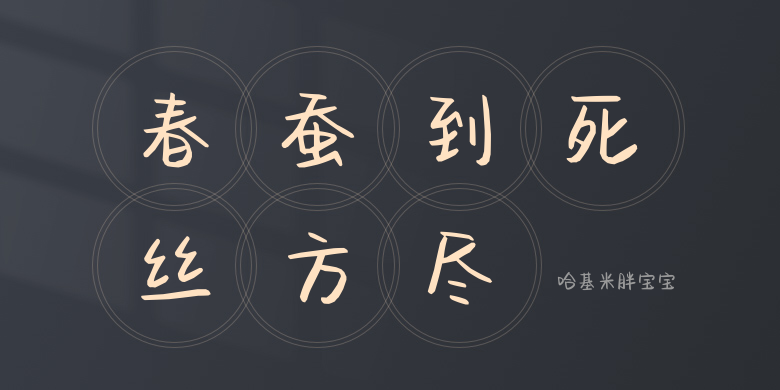
哈基米胖宝宝
哈基米胖宝宝,这款字体结构工整、笔画清晰,兼顾美观与易读性,适用于标题、正文、海报、包装、LOGO 等多种场景。字形优雅稳定,风格百搭耐看,适配日常排版与创意设计,让文字呈现更舒适、更具质感。哈基米胖宝宝一笔一画,皆是细节,以均衡的比例、流畅的线条打造舒适视觉体验,字形端正大气,风格简约现代。无论是商业设计、品牌宣传还是日常排版,都能轻松驾驭,让文字更有格调与力量。哈基米胖宝宝字体下载。